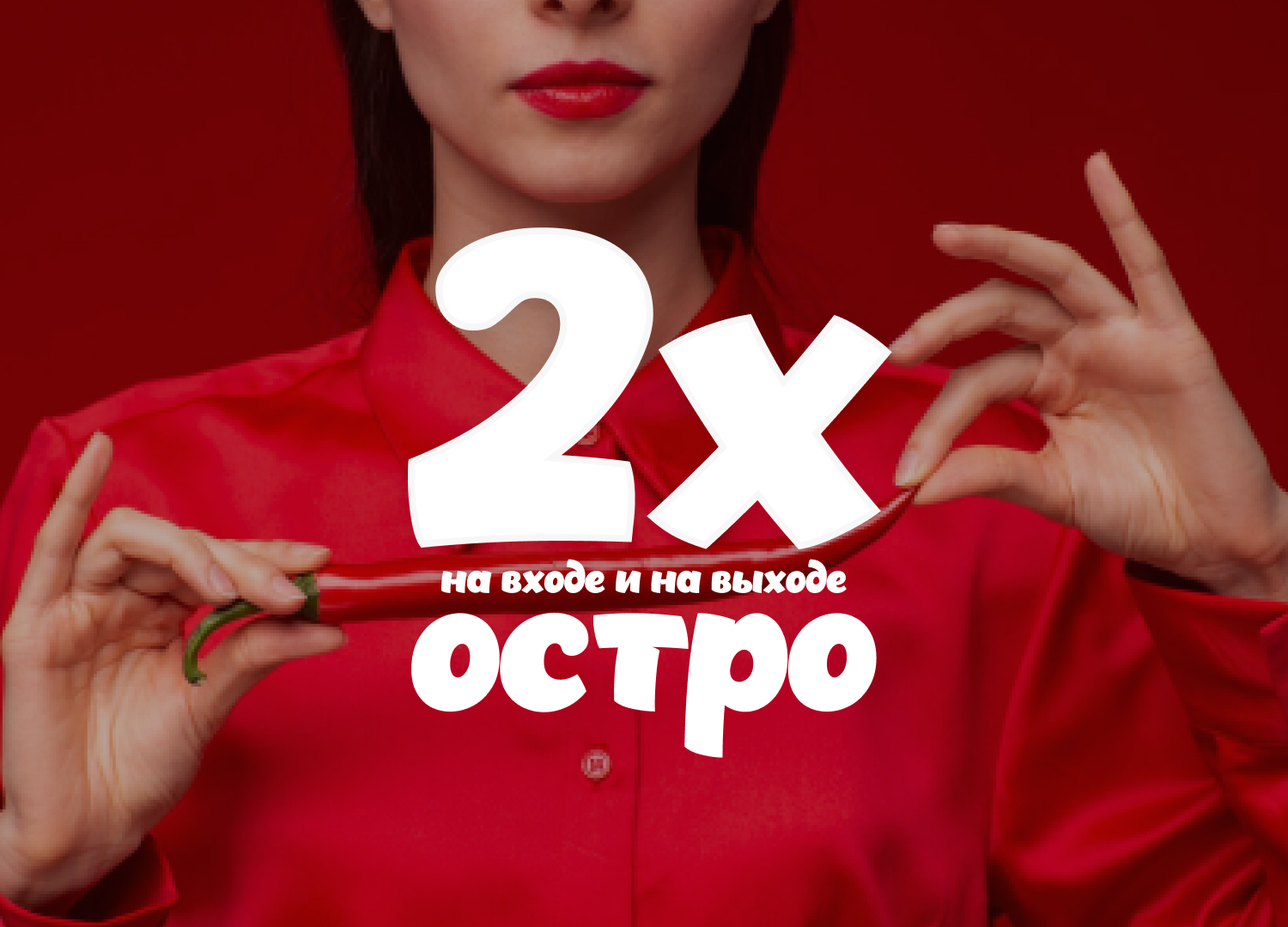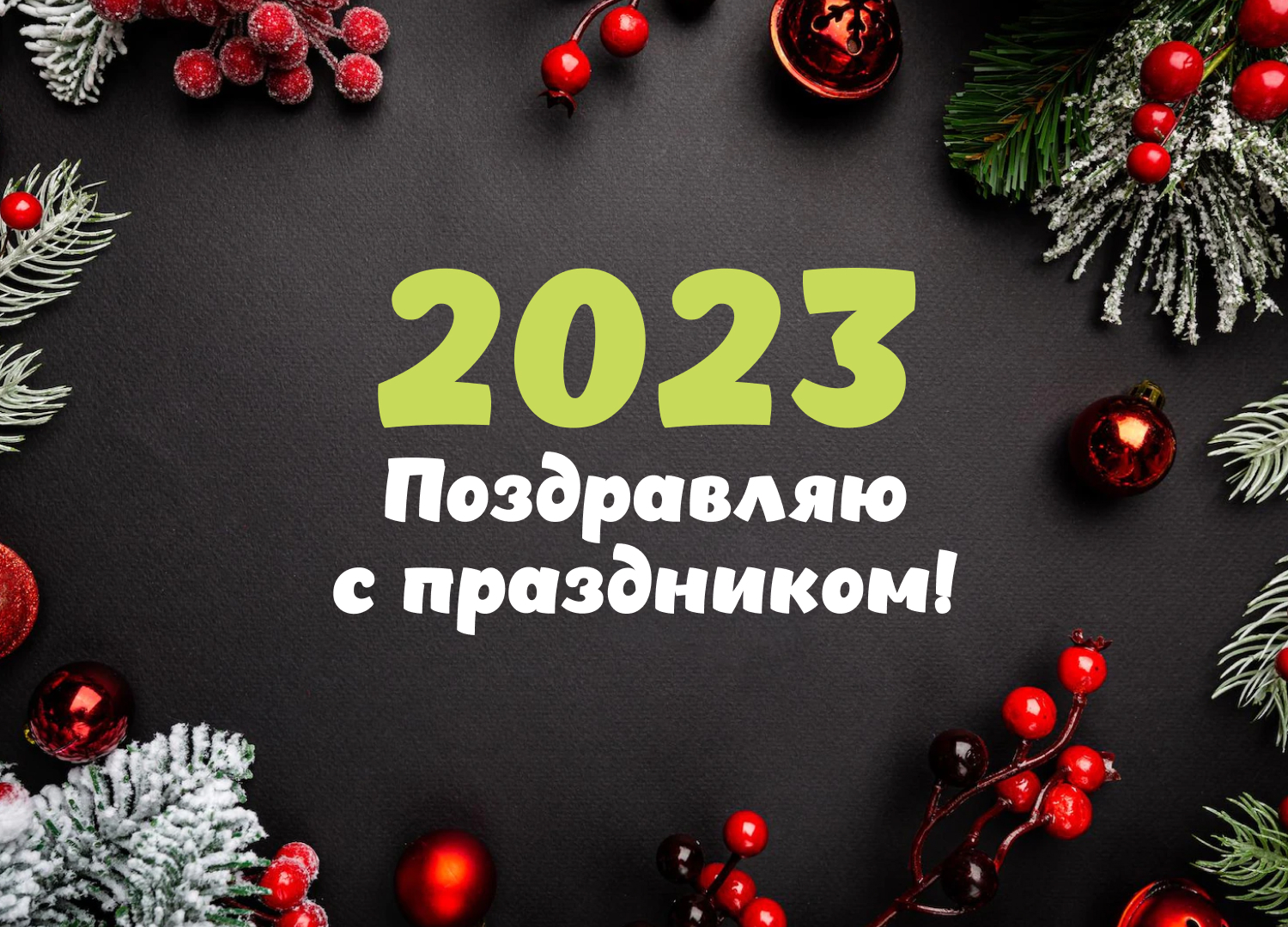
Бесплатный шрифт. Chekharda
Чехардаааа! Классный, пухлый и вполне читаемый декоративный шрифт. Идеально для всяких праздников, детских тематик и вкусностей. Ном-ном-ном. Полностью бесплатный